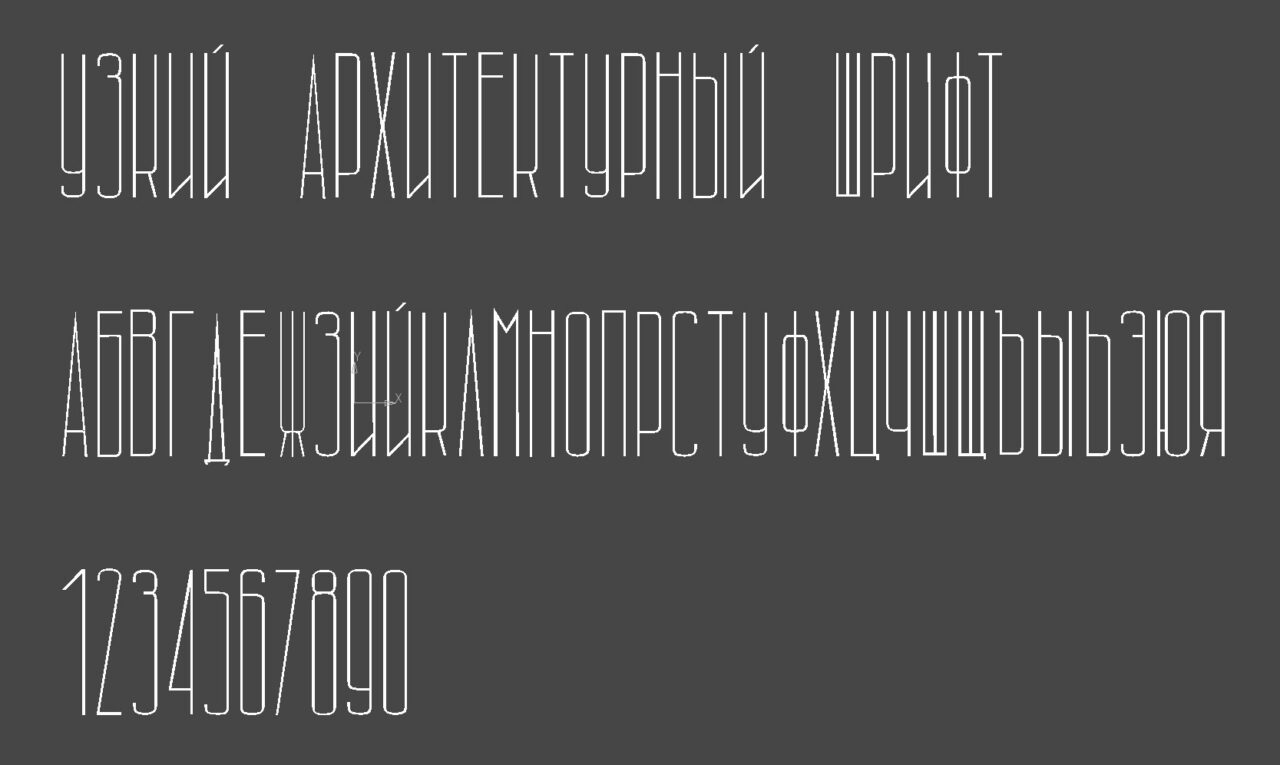
Узкий архитектурный шрифт в формате ttf, 5 к 1. Подойдет для любых программ, autocad, КОМПАС-3D и т.д. В жирном варианте начертание не очень смотрится.
Узкий архитектурный шрифт